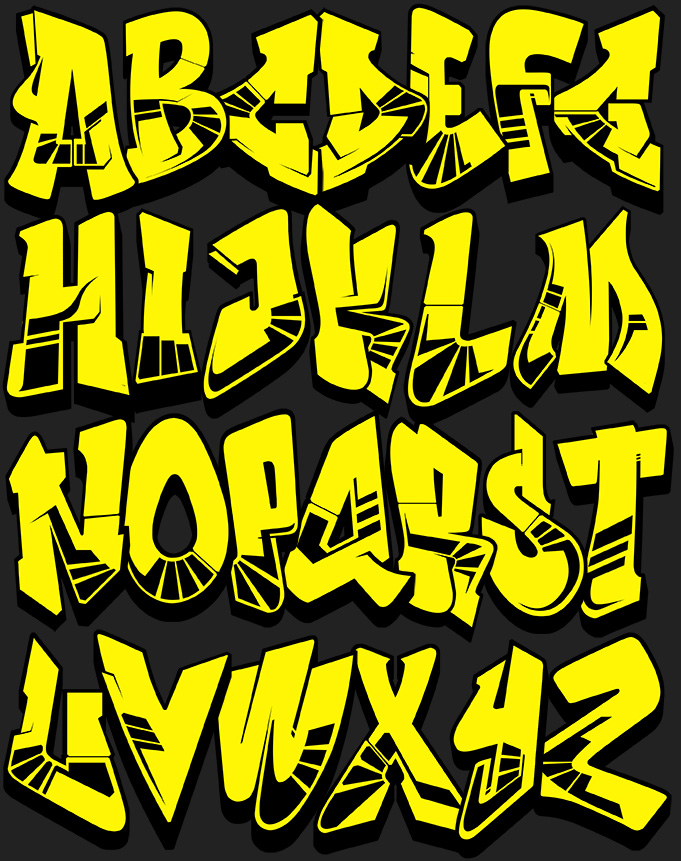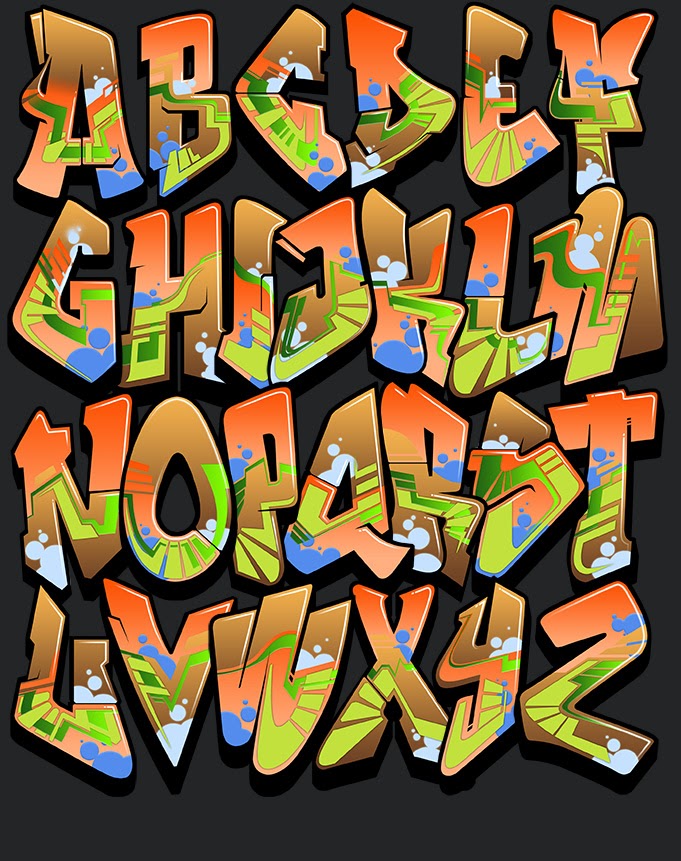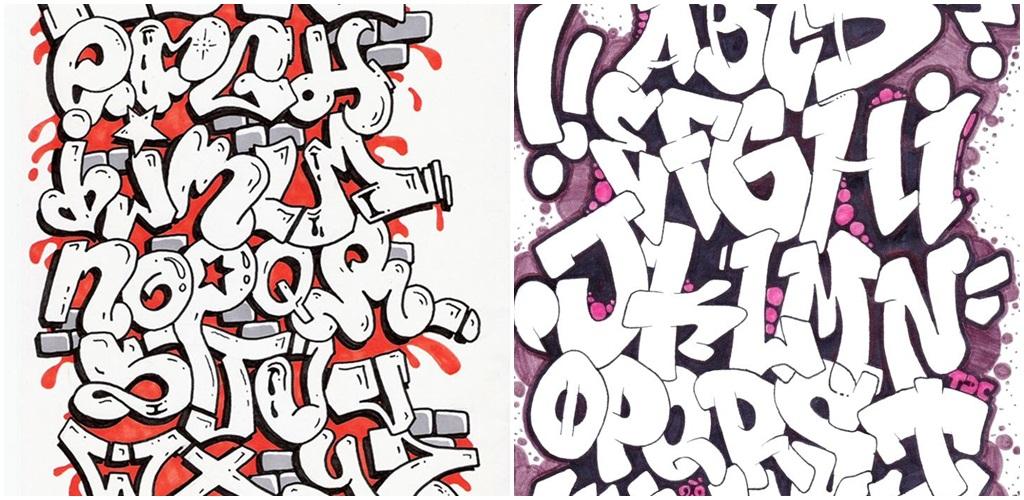
Рукописные — Граффити шрифты — Fontzzz.
The modern art form of Graffiti was developed in the late 70’s in New York and began with words that were designed and then copied onto walls and on trains. Graffiti is a form of expression that has been used throughout history, both for artistic use and for political reasons. The letter designs in graffiti nowadays are hip, cool and designed to stand out to a younger crowd. Graffiti art and culture is usually associated with the suburbs and with underground music such as Hip-hop and Electronic Dance music. Download some free graffiti fonts here and add a cutting edge style to your designs. A selection of fun and interesting fonts is available here for free and without the need to register.
Русский алфавит в граффити.
Семь кириллических шрифтов граффитиМногие райтеры имеют свой стиль и придумывают самостоятельно . Но все равно существуют основные принципы и шрифты, которыми пользуется большинство.
Я тоже иногда придумываю свои буквы и зарисовываю их на бумаге, во-первых, чтобы не забыть, а во вторых, воспроизводить на стене знакомый шрифт потом легче, чем изобретать что-то на ходу.
Самые распространенные стили написания и буквы граффити
Баббл
Такие мультяшные объемные буквы – самый распространенный вариант. В шрифте баббл буквы должны сливаться и как бы наплывать друг на друга. Единственный минус – иногда прочитать, что написано в этом стиле довольно трудно, так как буквы могут искажаться практически до неузнаваемости.
Блокбастерс
Для этого стиля граффити нужно сначала нанести на поверхность тон. Лучше сделать это при помощи валика, но можно и баллоном. Это работа не для одного и лучше выполнять ее вместе с товарищами.
На фон наносятся ровные и четкие буквы граффити. Многие райтеры используют блокбастерс как свой фирменный стиль.
Вайлд
В этом стиле буквы граффити практически невозможно прочитать. Здесь можно проявить фантазию по полной программе. Буквы можно путать, дополнять их любыми элементами и сплетать самым невообразимым образом. Вайлд – довольно сложный авторский шрифт.
FX
Объемный граффити стиль и довольно сложный. Буквы в данном случае требуют тщательной проработки. Не советую новичкам пытаться начинать с него. Все равно ничего дельного не получится.
Мессия
Эти граффити буквы придумали в Америке. Многослойный шрифт с эффектом наложения изображений. Тоже не самый легкий вариант, который используют довольно опытные райтеры. Такие буквы граффити не нарисуешь за 15 минут.
Характер
Это уже даже не буквы, а целая картина. Нарисовать ее можно только при наличии разных насадок. Обычно в характере изображают героев комиксов.
Throw up